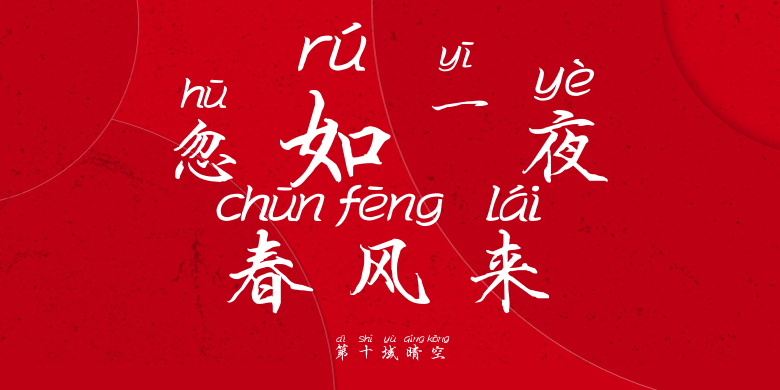
第十域晴空
第十域晴空,这款字体结构工整、笔画清晰,兼顾美观与易读性,适用于标题、正文、海报、包装、LOGO 等多种场景。字形优雅稳定,风格百搭耐看,适配日常排版与创意设计,让文字呈现更舒适、更具质感。第十域晴空一笔一画,皆是细节,以均衡的比例、流畅的线条打造舒适视觉体验,字形端正大气,风格简约现代。无论是商业设计、品牌宣传还是日常排版,都能轻松驾驭,让文字更有格调与力量。第十域晴空字体下载。